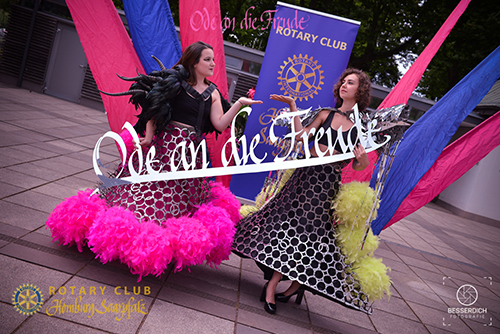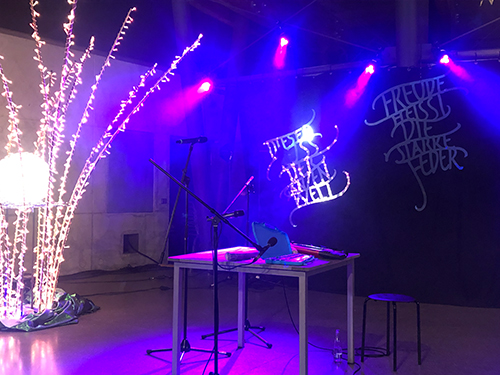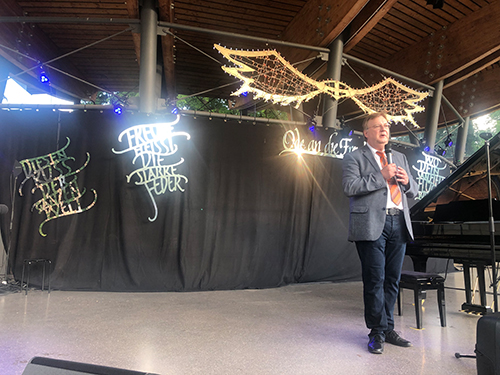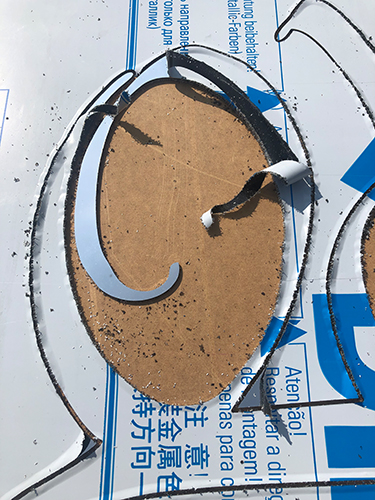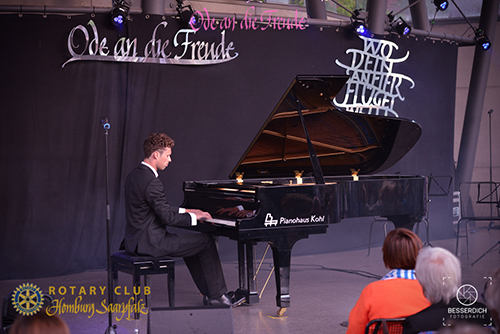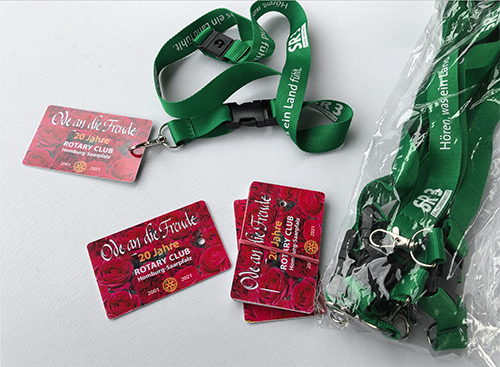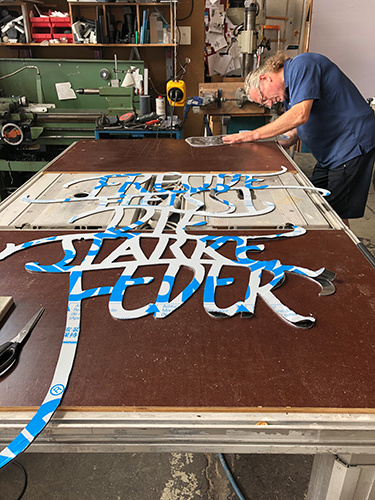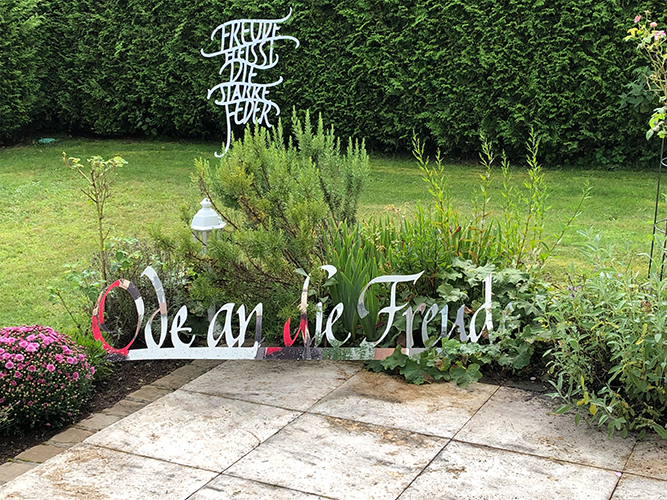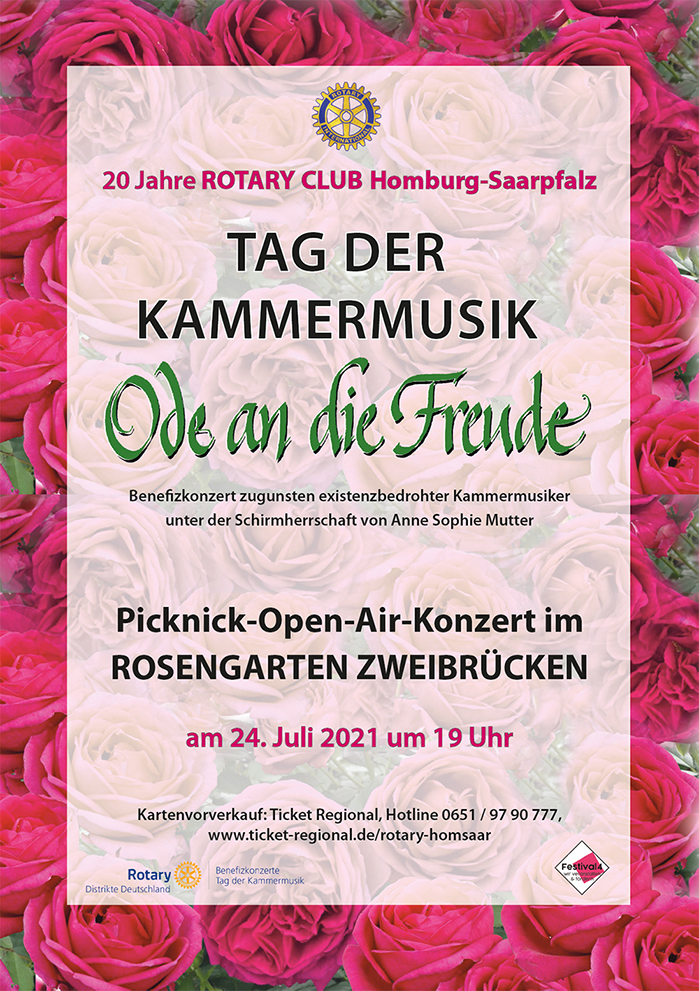
Am 24. Juli 2021 fand in Zweibrücken ein Konzert der Extraklasse statt. Ich hatte die wunderbare Gelegenheit, die grafisch-kalligrafische Gestaltung für dieses Konzert zu machen. Nicht nur Plakat, Tragetaschen, Programmheft und weitere Drucksachen, sondern Schriftzüge, die aus Alu Dibond ausgeschnitten und auf der Bühne eingesetzt wurden, hatten kalligrafischen Charakter. Jochen Maas, der sich für das Gesamtkonzept auszeichnet, die Agentur Mediakreativwerk in Saarbrücken, Fa. Peehs Kunststoffe in Bexbach, der Rotaract Club Saarbrücken und weitere Personen und Firmen trugen zu einem unvergesslichen Konzertabend bei. Die Musiker, die diesen Abend zu einem Feuerwerk werden ließen, waren das Feuerbach-Quartett, der Pianist Rick-Henri Ginkel, die Mezzosopranistin Carmen Seibel und Opernsänger Charles Dekeyser (B). |
Das Plakat wurde auch die Titelseite der Programmbroschüre, deren Innenteil von der Firma Mediakreativwerk fertiggestellt wurde.
Das Logo "Ode an die Freunde" kam in vielerlei Hinsicht zur Anwendung. Auf der Tragetasche, die mit Picknickutensilien für jeden Zuschauer gefüllt war, einschließlich Regencape, von dem zu Beginn des Konzerts reichlich Gebrauch gemacht wurde. Auf der Bühne im Rosengarten Zweibrücken fand das Logo in 2 Meter Breite seinen Platz unter den Flügeln von Jochen Maas. Zwei Schönheiten in Kostümen von Jochen Maas trugen den Schriftzug, der mit einer durchgehenden Linie verstärkt wurde, damit er aus dem Aluminium-Dibond ausgesägt werden konnte und am Stück blieb, boten die Umrahmung für die Personenfotos zu Beginn des Konzerts. Die andren Schriftzüge, bei denen es sich um Textpassagen aus der Ode an die Freude handelt, waren ursprünglich gedacht für eine Hängung in den Bäumen des Rosengartens und sind auch dafür konzipiert. Wetter und Zeit gaben den Schriftzügen einen anderen Platz direkt hinter den Musikern. Für die Zukunft ist aber noch einiges geplant! |
Das Feuerbach-Quartett auf der Bühne im Zweibrücker Rosengarten /links), rechts der junge Pianist Henri.
Bis kurz vor dem Konzert wurde in der Firma Peehs in Bexbach an den Schriftzügen gearbeitet
Derzeit haben die Schriftzüge aus dem verspiegelten Alu-Dibond einen Platz im Garten der Stiftung Schriftkultur bekommen.